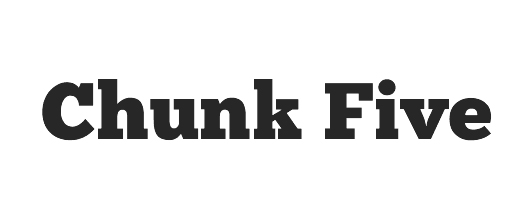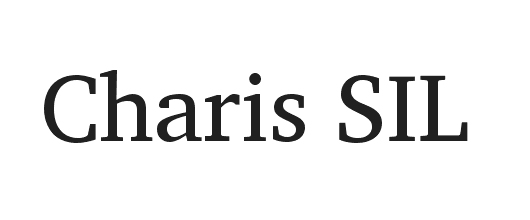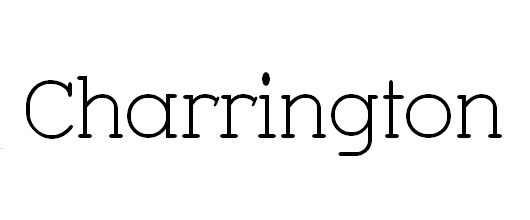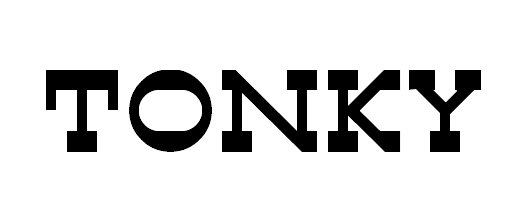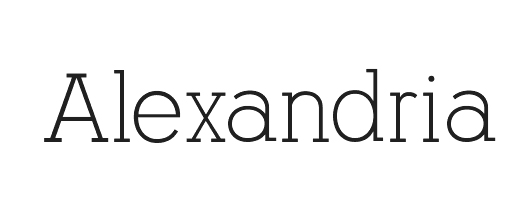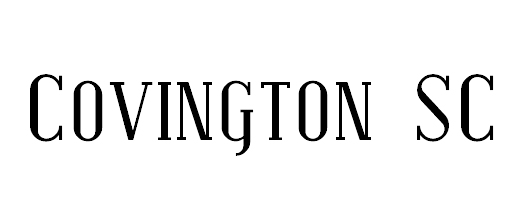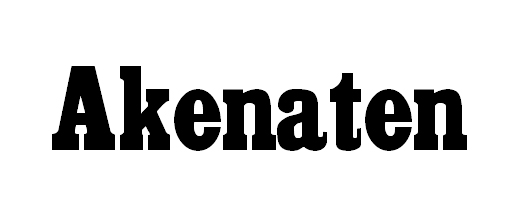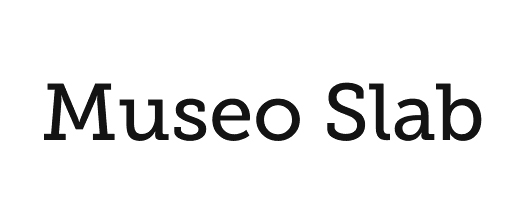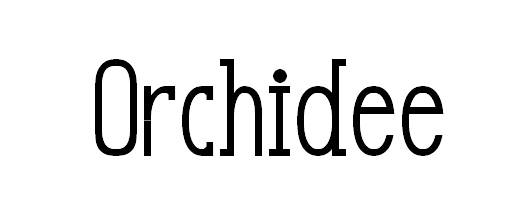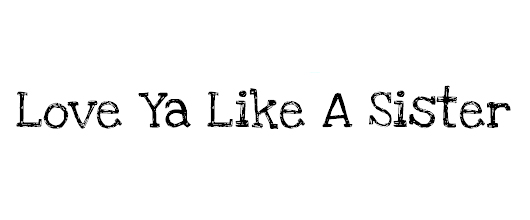
Serifenbetonte Schriften, auch SlabSerif Fonts genannt, sind super für Logos, Überschriften oder Slogans geeignet, und man kann sie immer wieder auf modernen Webseiten im Einsatz bewundern. Kostenlose serifenbetonte Schriften gibt es jede Menge, daher habe ich dir meine Lieblings- SlabSerifen zusammen gestellt.
1. Chunk Five
2. Charis SIL
3. Charrington
4. Tonky
5. Alexandria
6. Covington SC
7. Akenaten
8. Museo Slab
9. Orchidee
10. Love Ya Like a Sister
11. Kontrapunkt
12. Nadia Serif
13. Rough Rockys
14. Academic M54
15. Lifestyle Marker M54
Slab Serifen im Einsatz
Hier einige schöne Beispiele für die Verwendung von SlabSerifen im Webdesign.
1. Second And Park
2. Brookyn Fare
3. Jeroen Homan
Ich finde serifenbetonte Schriften total super, besonders für Headlines.
Wiedereinmal die Chunk Five ist mein Favorit ;-) oder eigentlich (die ist aber keine Free-Font, leider!) die Clarendon.
Mir gefällt die Lifestyle Marker – Schrift. Man muss mehrfach hinschauen, dass macht sie interessant. Freue mich schon auf weitere,tolle Schriften!
Vielen Dank für diese tolle Liste. Mir gefallen Serifenschriften auch sehr. Am besten gefallen mir Chunk Five und Love Ya Like a Sister :) Ich wünsche euch ein wunderschönes Wochenende!
Chunk Five finde ich auch klasse, und die Museo Slab gehört auf jeden Fall auch ganz oben auf die Liste!